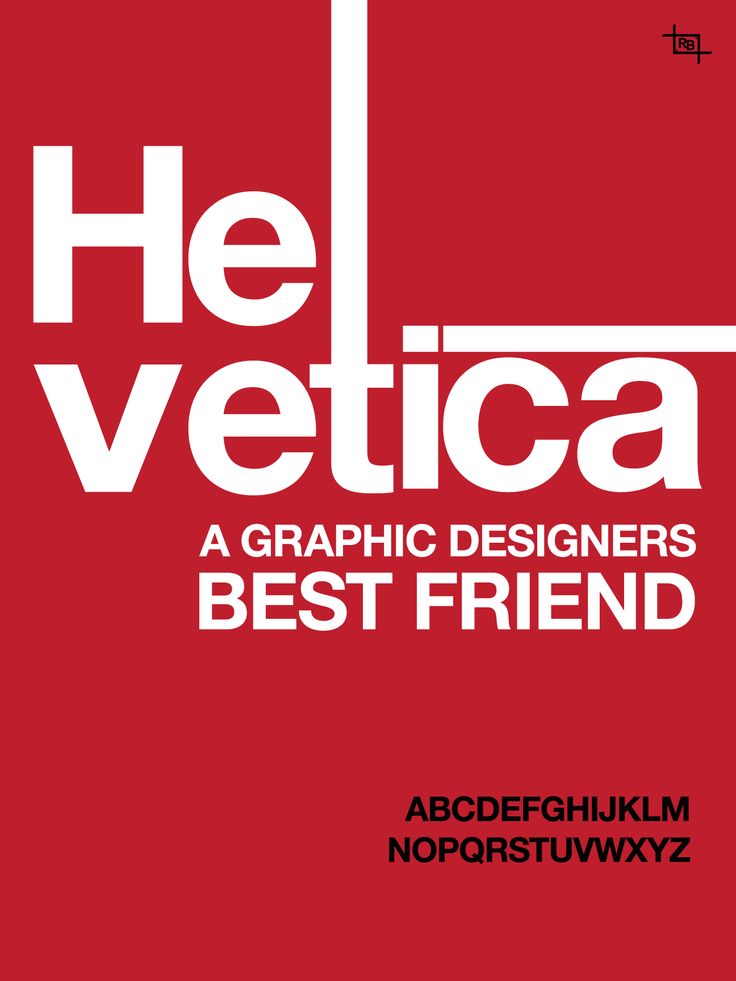
bibliographies — Helvetica for latin characters in a mixed document with latin and cyrillic — TeX
I have a document with English and Russian in both the main document and in the citations. For the latin characters I want to set Helvetica. But since Helvetica and/or the T1 encoding is not available in cyrillic the compilation of the cyrillic text fails. In the example below I tried adding additional encodings to overcome the problem, but with no success. The font of the cyrillic text is less important — it can be any sans serif font.
Simplifying, by using unicode-math package, and also:
Since Babel package can use Lualatex’s ability to auto-detect scripts, and, with Lualatex’s ability to use TrueType/OpenType system fonts, there is no longer any need to employ 8-bit fonts from last century with their encodings.
Neue Helvetica Cyrillica: ru_font — LiveJournal
?Есть у кого-нибудь полный набор новой хельветики кирилической(34 написания)? Было бы круто если OTF.
Но на самом деле не важно какой формат.
Arial и Helvetica — разница и сравнение
История шрифтов Arial и Helvetica
Arial изначально был известен как Sonoran Sans Serif и стал известен как Arial после его включения в Windows Microsoft. Версии 2.76 и более поздние версии включают глифы арабского (не курсивного) и иврита. Версии 5.00 поддерживают латиницу C, латиницу D, расширенный греческий язык, кириллицу и коптские символы. В настоящее время Monotype владеет авторскими правами на шрифт Arial.